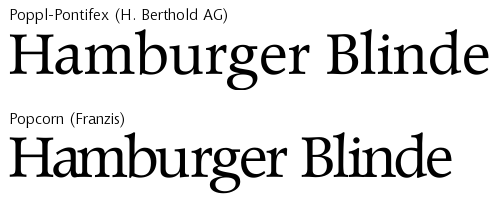
Aber in einem anderen Thread war auch die Rede von einer "Bitstream 500 Font CD".
Gibt es auch gute, günstige, empfehlenswerte Sammlungen? (Diese Bitstream-CD habe ich über Google bei keinem Händler entdeckt...)
Die Bitstream-500-Font-CD ist eine gute, brauchbare Sammlung, die mir immernoch gute Dienste leistet. Sie ist aber auch schon recht alt, und die Schriften sind nach heutigem Verständnis nicht gut ausgebaut (keine Kapitälchen, kaum Ligaturen) und daher auch nur mit gewissen Einschränkungen verwendbar.
Ein Teil der Bitstream-Schriften sowie einige Schriften aus anderen Quellen wird auch mit Corel Draw ausgeliefert, allerdings unter anderen Namen. Ulrich Stiehl hat die Corel-Draw-Schriften hier dokumentiert: http://www.sanskritweb.net/cdrfonts/
Er schreibt, Corel Draw 9 enthalte die meisten Schriften, Du könntest also mal schauen, ob Du das irgendwo günstig bekommst. Wie rechtmäßig diese Schriftklone von Corel sind, kann ich Dir aber leider nicht sagen.
Der Franzis-Verlag bietet eine günstige Schriftsammlung (unter versch. Namen, z.B. „Schriftenbibliothek“) an, die einen Teil der Schriften der ehemaligen Firma Berthold enthält. Diese Sammlung ist nicht zu empfehlen, da bei den Schriften (warum auch immer) die Buchstabenabstände unbrauchbar sind.
Softmaker bietet ebenfalls eine günstige Sammlung mit Schriften von Berthold und aus anderen Quellen an („Megafont XXL“). Zu den Schriften kann ich nichts sagen; möglicherweise sind sie mit den Franzis-Schriften identisch und somit nicht zu empfehlen.
Die Frage ist, ob die Infinitype-Schriften sich irgendwie von den Megafont-Schriften unterscheiden, abgesehen davon, daß sie zusätzlich zum Truetype-Format auch noch als Postscript-Schriften enthalten sind.
Ulrich Stiehl schreibt (allerdings zu Infinitype 2.0):
Under the label "infiniType 2.0", Mr. Martin Kotulla sells a small selection of the fonts contained on the MegaFont XXL CD, as both TrueType and PostScript Type 1 fonts, to the target group of customers who want to pay more money for fewer fonts
(bsp. ITC Handel Gothic = Huntington), den kann ich verstehen wenn er dort zuschlägt.
sicher sind die fonts nicht alle aktuell und entsprechen nicht dem heutigen standard, es ist sind mehr
oder weniger musthave fonts, oldies. gut wenn man mal schnell einen schriftzug nachbauen muss.
würde ich heute ein CD entwerfen würde ich kaum auf eine der schriften zurückgreifen.
Bedeutet nur für "Windows und Linux" in diesem Zusammenhang, dass das Fitzelchen Software, das die Schriften gemeinsam installiert nur auf diesen OSn läuft oder verstehe ich da etwas nicht? (Hab 'nen Mac.)
PostScript für PC läuft nicht auf Mac. TrueType für PC (.ttf) jedoch ohne Probleme.
Ich würde einem Mac-Benutzer sogar raten, die Win-TTF-Version statt der Mac-PostScript-Version zu benutzen.
Kleine Ergänzung:
Die Adobe-Programme können unter OSX auch Windows-Postscript-Fonts selbstständig (d.h. ohne die Hilfe des Systems) verwenden. Hilft in Notfällen, aber ist natürlich nicht empfehlenswert, wenn man Schriften frisch kaufen will.